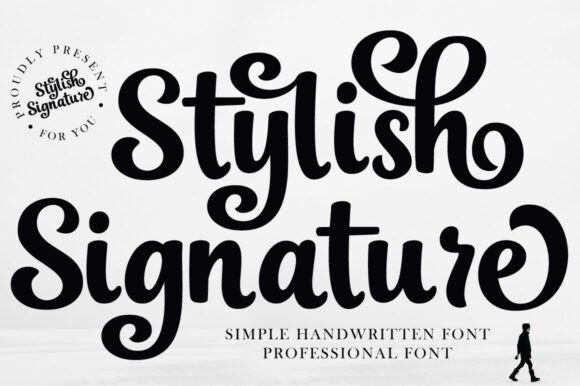
Stylish Signature
์˜ฌ๋ฐ”๋ฅธ ๋””์ž์ธ ์š”์†Œ๋ฅผ ์ฐพ๋Š” ๊ฒƒ์€ ์–ด๋ ค์šธ ์ˆ˜ ์žˆ์ง€๋งŒ Stylish Signature๋Š” ์ž‘์—…์„ ์ฆ‰์‹œ ํ–ฅ์ƒ์‹œํ‚ค๋Š” ๋›ฐ์–ด๋‚œ ์ปฌ๋ ‰์…˜์„ ์ œ๊ณตํ•ฉ๋‹ˆ๋‹ค.
์ •๋ฐ€ํ•˜๊ฒŒ ์ œ์ž‘๋œ Stylish Signature๋Š” ๊น”๋”ํ•œ ๋ฒกํ„ฐ, ๋ถ€๋“œ๋Ÿฌ์šด ํƒ€์ดํฌ๊ทธ๋ž˜ํ”ผ ๋ฐ ์•ˆ์‹ฌํ•  ์ˆ˜ ์žˆ๋Š” ์ƒ์—…์šฉ ๋ผ์ด์„ ์Šค๋ฅผ ์ œ๊ณตํ•ฉ๋‹ˆ๋‹ค.
POD(์ฃผ๋ฌธํ˜• ์ธ์‡„) ์ œํ’ˆ, ๊ฒฐํ˜ผ์‹ ์ดˆ๋Œ€์žฅ ๋˜๋Š” ์†Œ์…œ ๋ฏธ๋””์–ด ๊ทธ๋ž˜ํ”ฝ์„ ๋งŒ๋“ค ๋•Œ Stylish Signature๋Š” ์ด์ƒ์ ์ธ ์„ ํƒ์ž…๋‹ˆ๋‹ค.